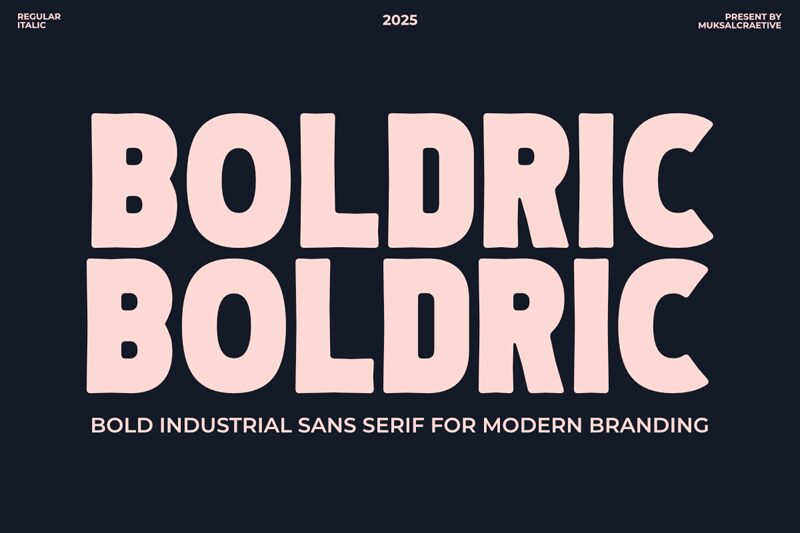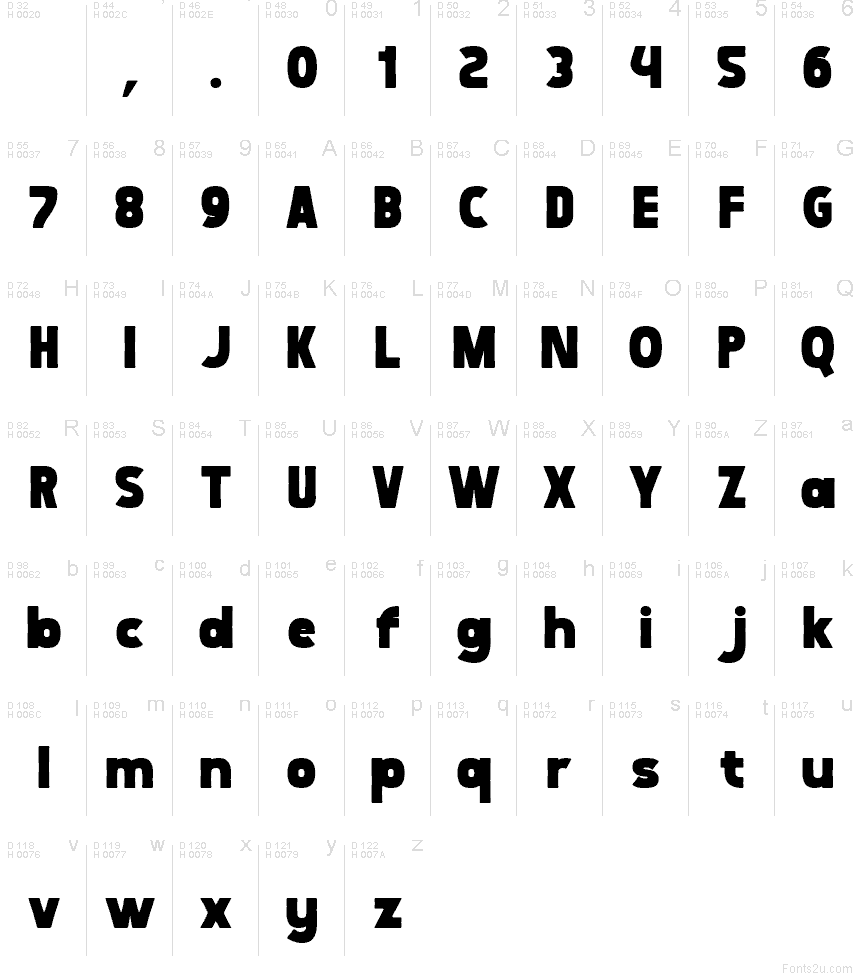
Boldric Regular
Boldric od Muksal Creative je bezplatné komiksové písmo so zaoblenými tvarmi a priateľským, kompaktným rytmom. Jeho široké a jednoduché znaky pôsobia ako ručne kreslené, no zároveň si zachovávajú čistotu. Dodávajú tak písmu jemnú, plastickú podobu, ktorá pôsobí živo, nie strnulo.
Boldric skvele poslúži pri titulkoch plagátov, v komiksových bublinách, na obaloch pre deti, herných banneroch, nálepkách aj grafike pre sociálne siete. Vďaka hladkým hranám a zjednodušeným tvarom zaručuje Boldric jednotný vzhľad a dodáva krátkym, výrazným textom jasný a neformálny charakter.